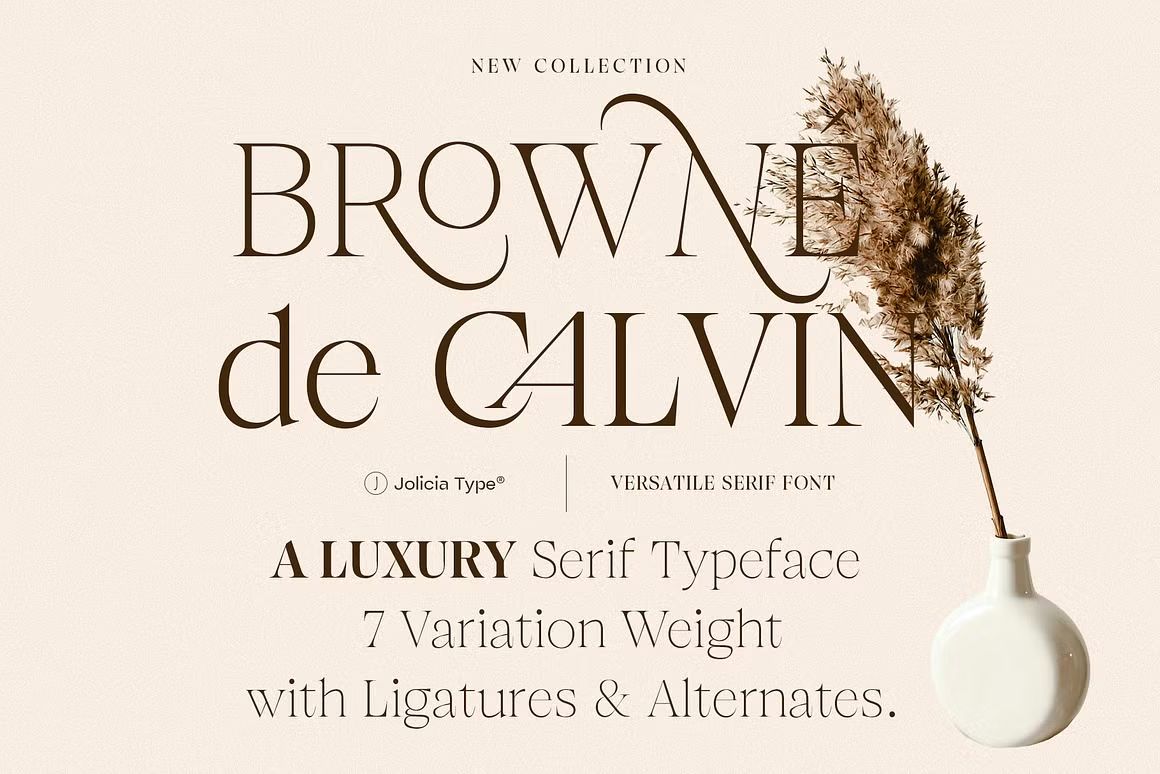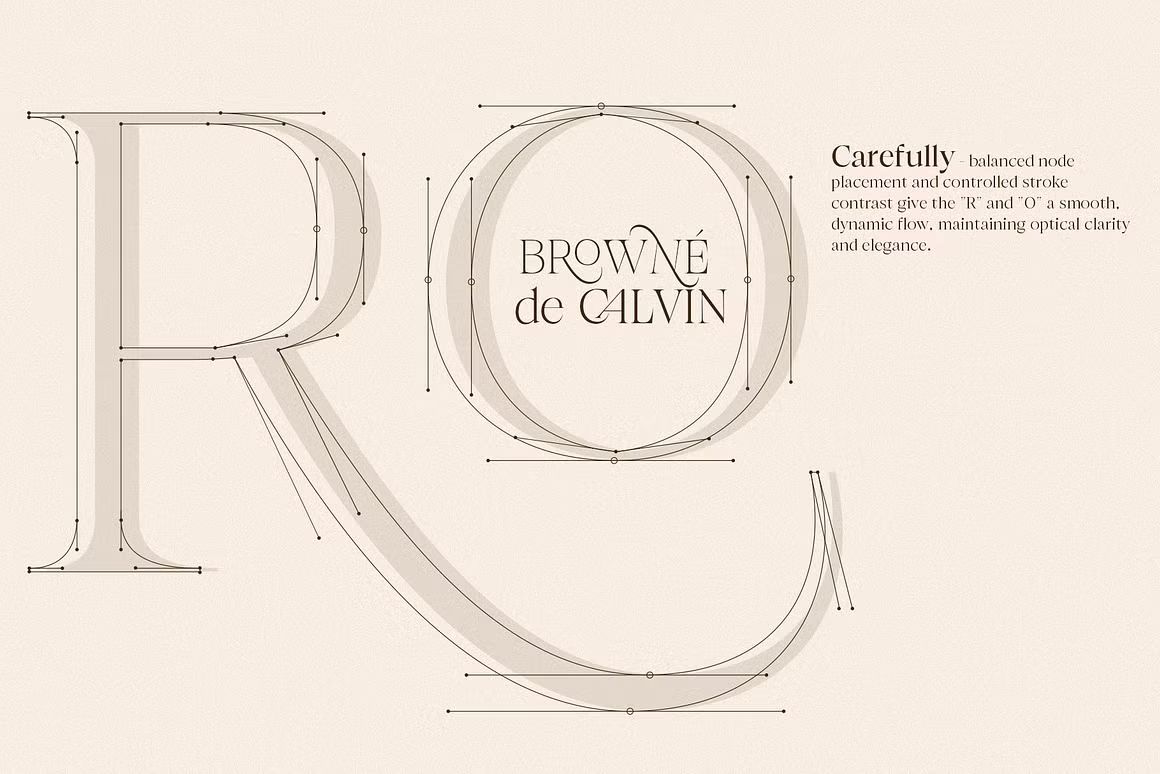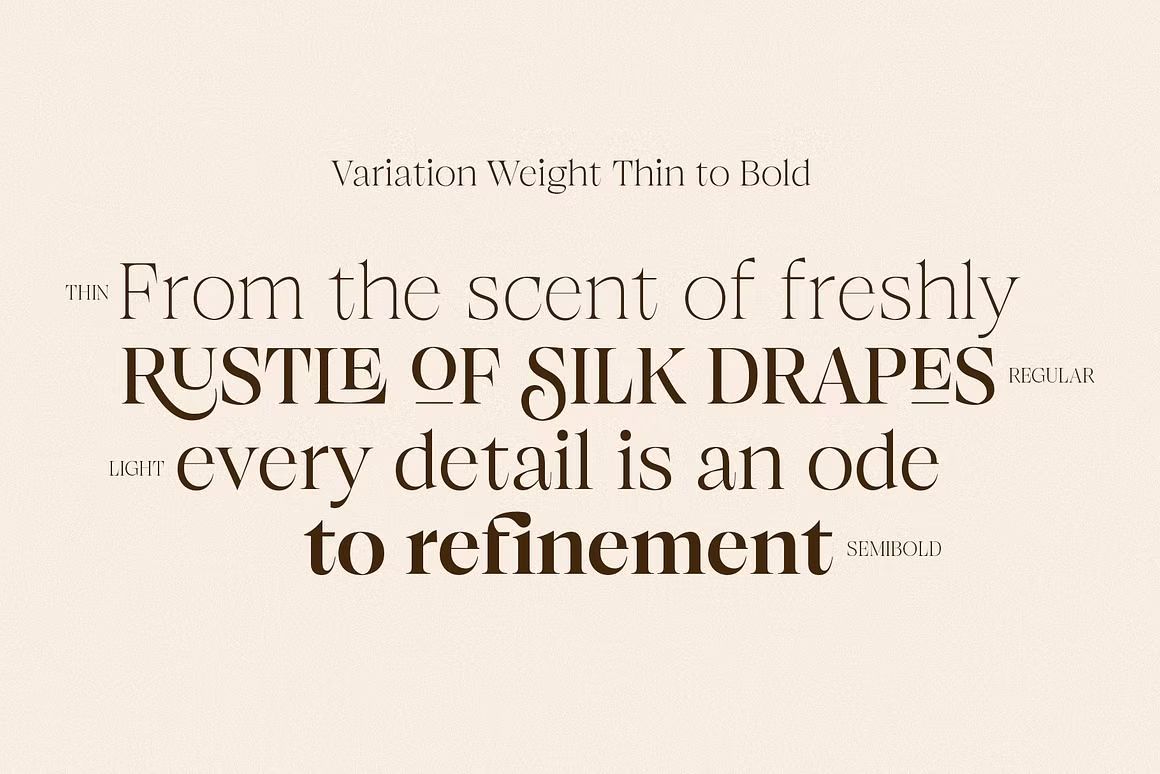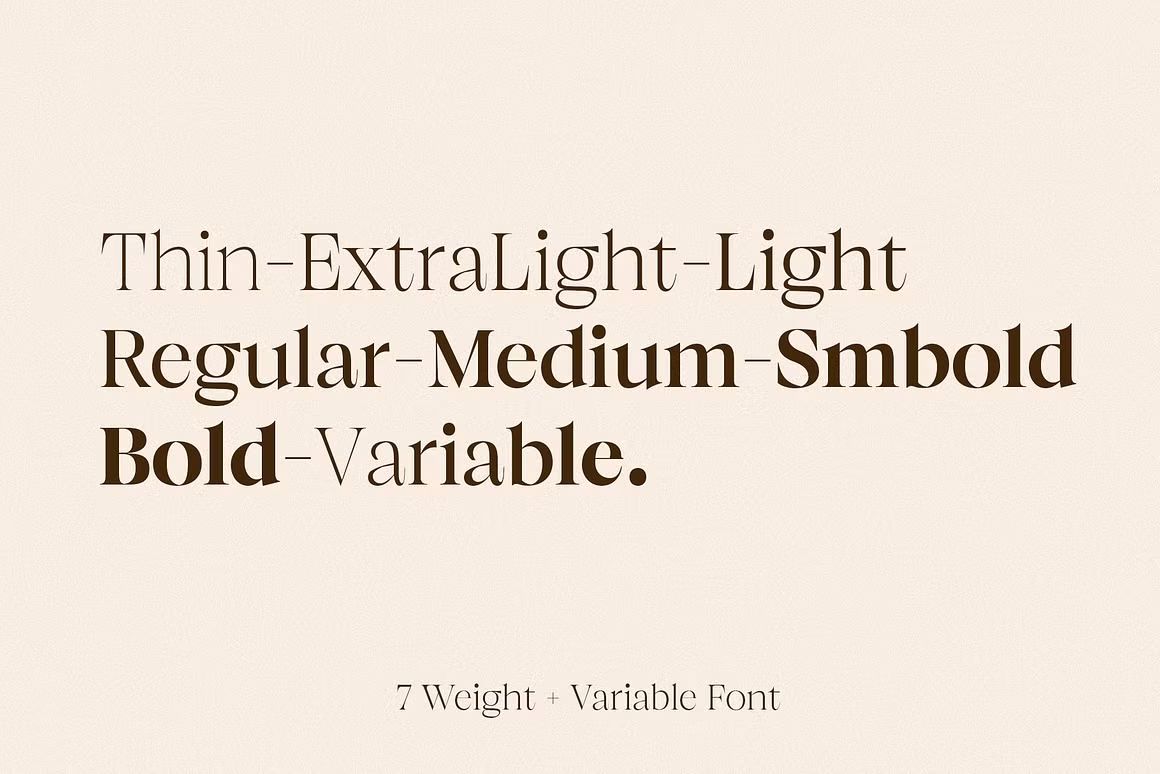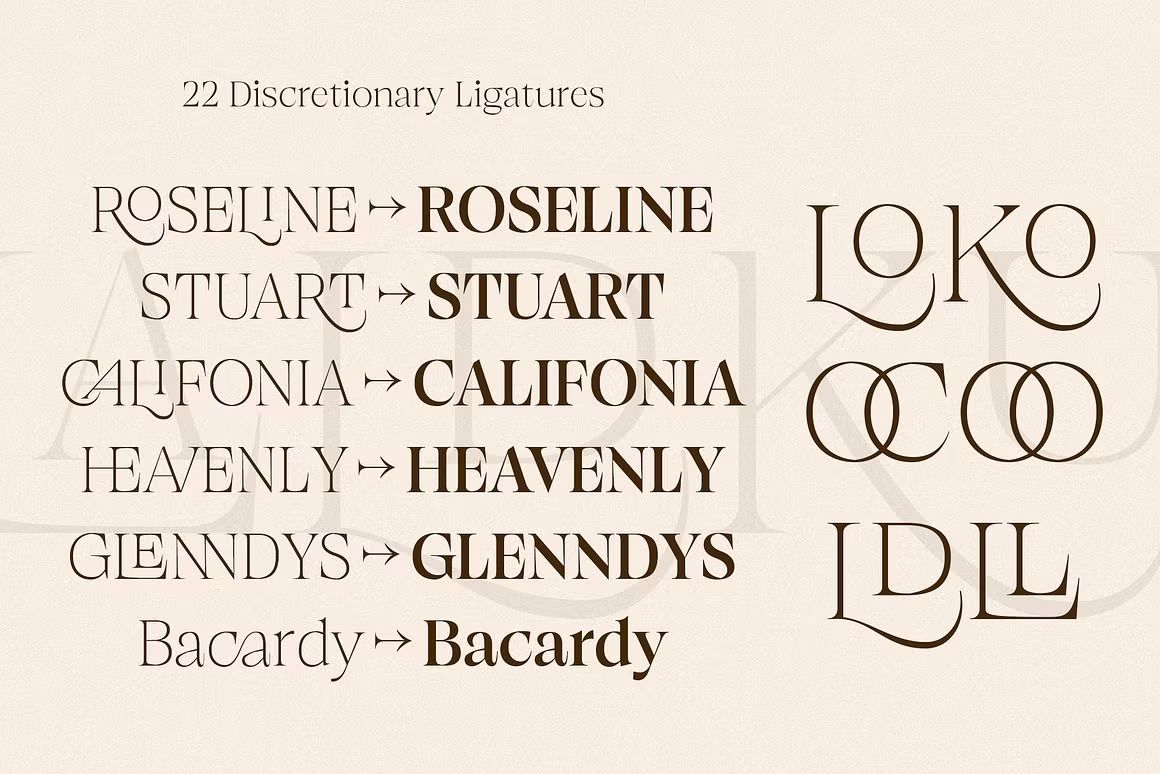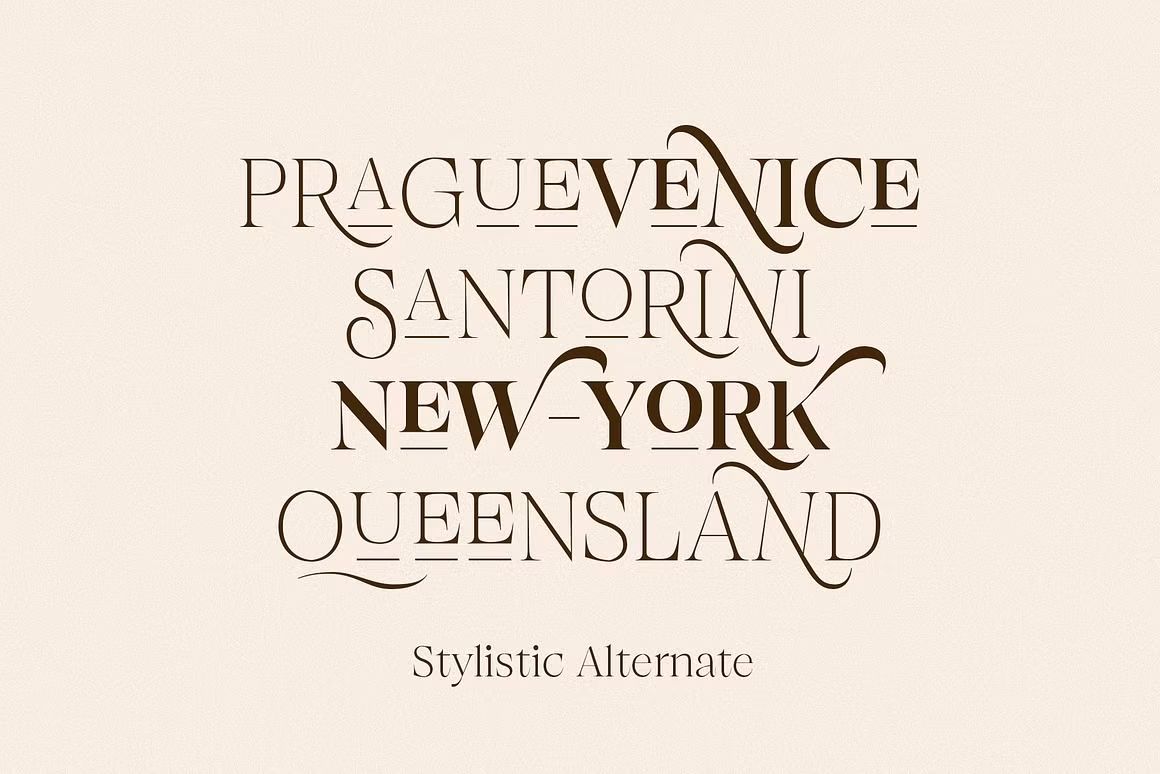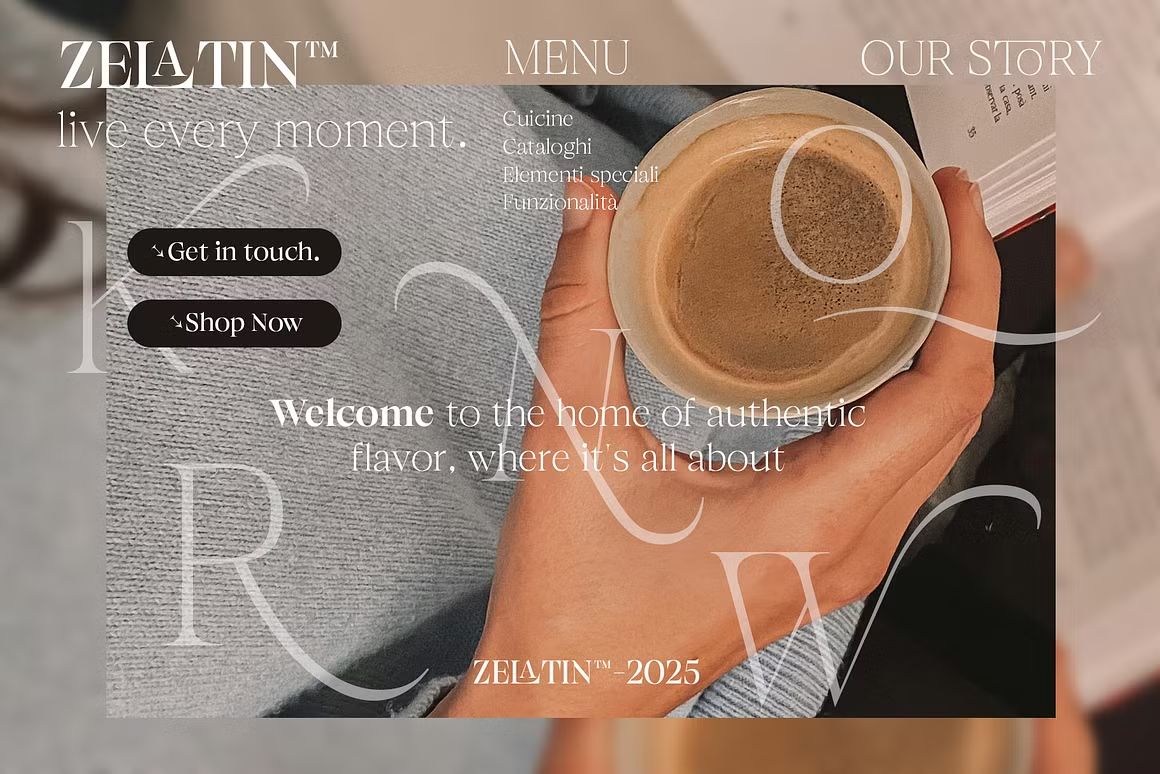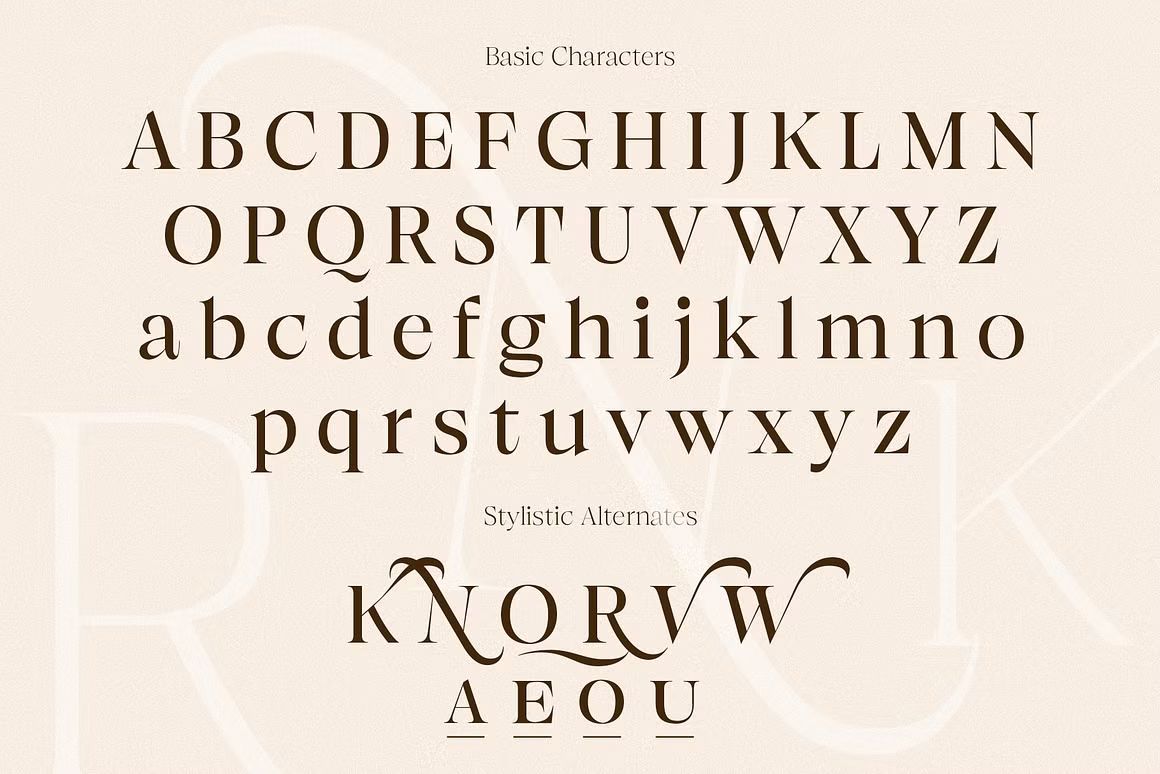
Browne de Calvin – Sans Serif Font
Browne de Calvin adalah font sans serif elegan dan minimalis, ideal untuk branding premium & editorial. Format OTF/TTF/WOFF, siap pakai di berbagai proyek desain.
Browne de Calvin adalah font sans serif modern dengan karakter tegas, bersih, dan berkelas. Menampilkan bentuk huruf yang proporsional dan minimalis, font ini cocok untuk branding mewah, editorial fashion, logo premium, kemasan, serta desain digital yang mengutamakan kesederhanaan elegan. Desainnya yang timeless menjadikan Browne de Calvin pilihan tepat untuk menciptakan identitas visual yang kuat dan profesional.
• Sans serif modern dengan kesan elegan & premium
• Ideal untuk branding, editorial, logo, dan kemasan
• Termasuk huruf kapital, kecil, angka, simbol, dan ligatur